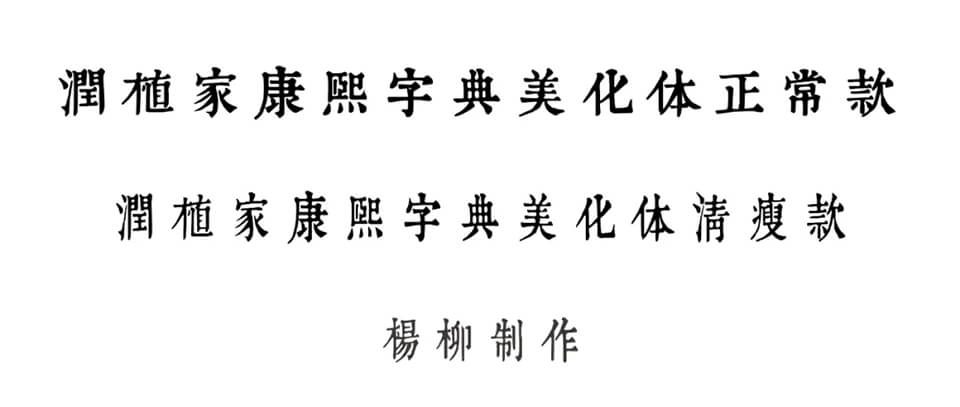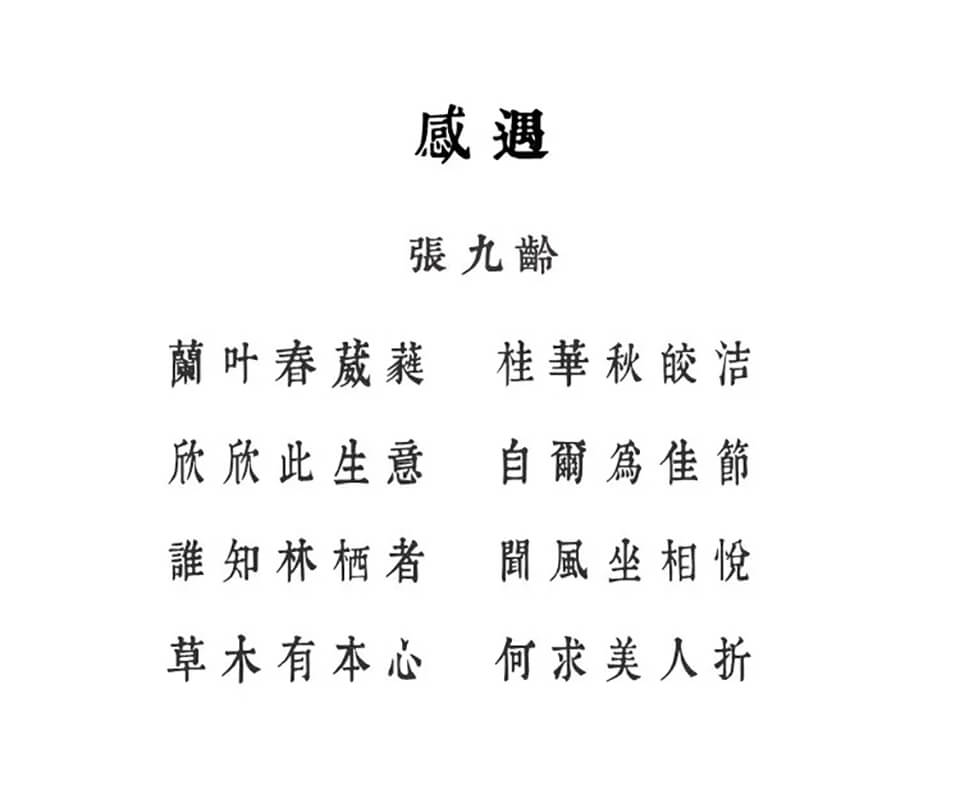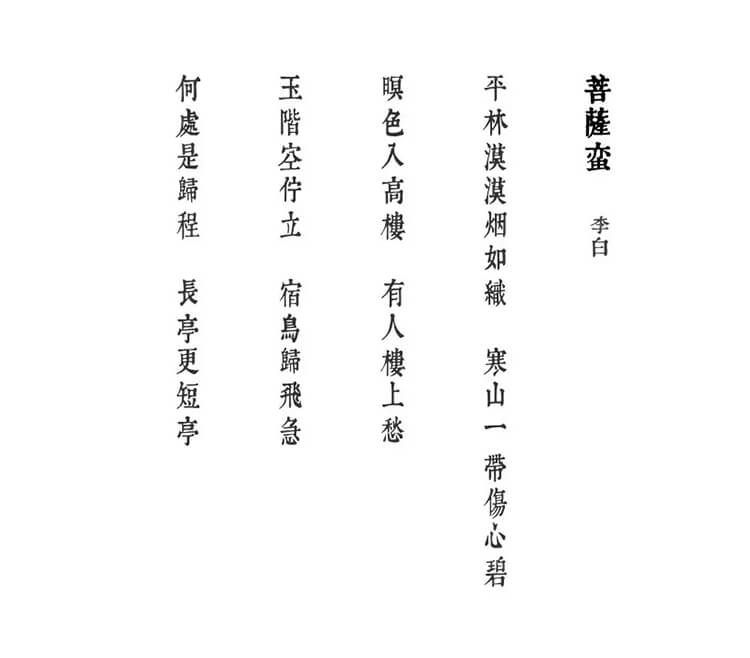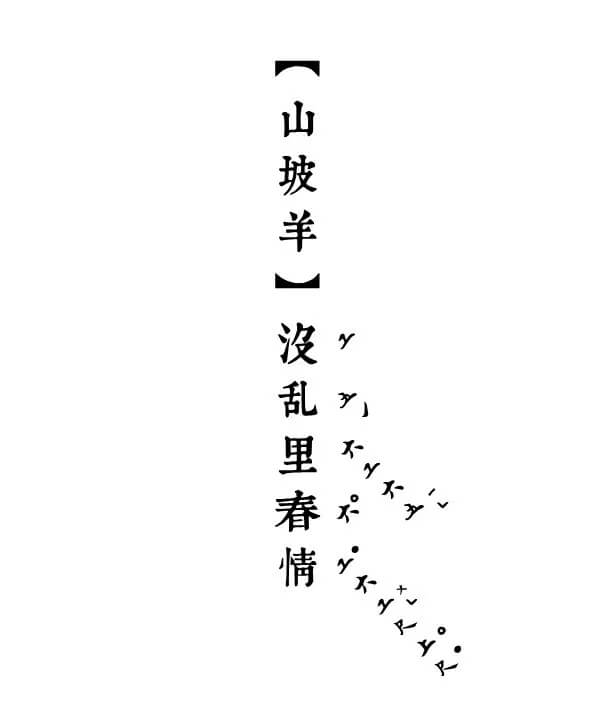
近日,我们又贡献出一个系列的免费可商用字体——润植家康熙字典美化体
包括两个子集:
1. 润植家康熙字典美化体正常款(也就是Regular款):常规使用,各种场景适应性好,尤其适合标题、少量文字的海报等。
2. 润植家康熙字典美化体清瘦款(可以视同Light款):作为辅助,或应用于重要的正文。
此前,网上有基于康熙字典的字体,康熙字典的字体也是许多文字编辑、平面设计工作者的大爱。不过可惜:其一,网上的康熙字典字体是不可商用的,且当前似乎已不对外提供了;其二,由于康熙字典的雕版古籍,有许多雕版印刷的磨损瑕疵,这些瑕疵一般都没有得到修复(尽管有古朴残缺之美,但是也毕竟与雕版原始字的意图相差甚远);其三,康熙字典作为繁体字库,有大量简体字是没有的,使用时需要先翻译成繁体字,而且,还有大量常用汉字没有对应繁体,也就是说,是完全不被康熙字典包含的。
我们提供的这套字体,基于康熙字典风格进行美化,有以下特点:
- 拓展了许多康熙字体没有的字。至少有上百个现代汉语常用字,在康熙字典中是没有的。润植家创始人杨博士,按照康熙字体的风格,人工生造而成,这样,可以用于许多现代语境的词汇输入,如“甭说”的“甭”、“垃圾”的“垃”、“多肽”的“肽”、“咖啡”的“咖”、甚至我们读者受众多是戏曲爱好者,戏曲中常见的“唢呐”的“唢”、“掭头”的“掭”,等等,大量的字并非繁体简体互换的问题,而是这些字根本就不存在于康熙字典之中。这类字都得到了生造补充。
- 印刷斑驳噪点充分修复。网上关于古籍的衬线字体,往往存在问题是:雕版印刷斑驳,破损噪点众多,但没有得到修复。我们这个字体对康熙字典进行了的斑驳修复,字体整洁如新。
- 美化处理:适当加粗美化,更端庄大气,适合字少的场景,比如作为海报标题使用。
- 美化处理:适当柔化笔触,增加一点点书法风格,弱化了一点康熙字典的金石刀篆风格,看起来更赏心悦目一点。
- 部分字形不美观的字,重新调整字形。
- 我们已为用户设置成自动转换繁体,不用再特地将简体转化繁体,直接输入简体,即可显示成康熙字典中对应的繁体字,使用更为方便。
用于诗词类场景(标题为正常款、正文用清瘦款)如下
用于诗词古文竖排场景(标题为正常款、正文用清瘦款)如下
与我们的润植家工尺谱字体,一起用于抄谱,也非常搭配哦!